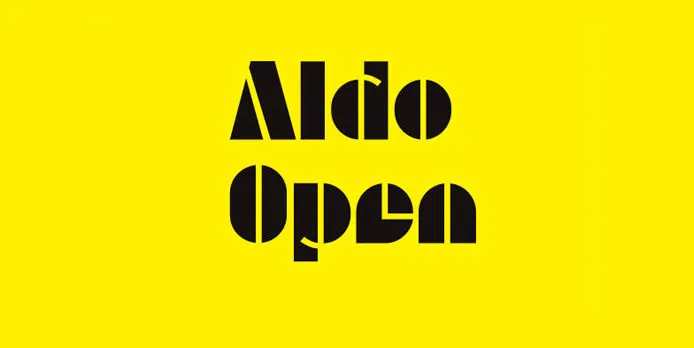
A Aldo Font Family é uma serifada robusta que reinterpreta estilizada a original cartaz do filme de 1970 “O Batalha pelo Planeta dos Macacos”. Inspirado nas letras de filmes de horror e sci-fi, essa fonte abrangente pode ser usada em diversas plataformas gráficas como impressão, web, motion design e até mesmo na criação de camisetas. Através da Aldo Open, os designers podem expandir o potencial desta tipografia vibrante para uma variedade de aplicativos do mundo digital ao papel. Com seu ar robusto e sua capacidade de adaptabilidade em diversos formatos gráficos, a Aldo Font Family é um recurso impecável para quem procura estilizar seus projetos digitais e físicos de maneira profissional e envolvente.